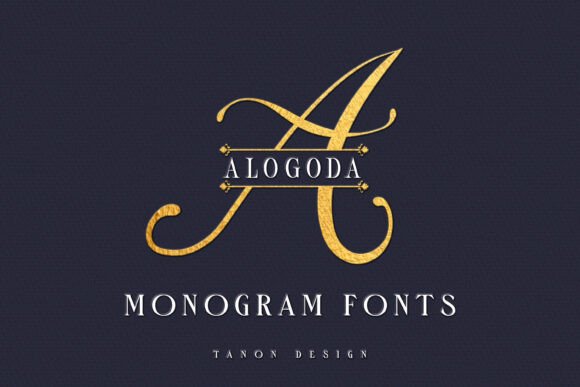
Alogoda Monogram
Alogoda Monogramのような高品質の素材をお探しの場合、このプレミアムパッケージはクリエイティブなプロジェクトに素晴らしい選択です。
POD(オンデマンド印刷)製品、結婚式の招待状、またはソーシャルメディアのグラフィックを作成している場合でも、Alogoda Monogramは理想的です。